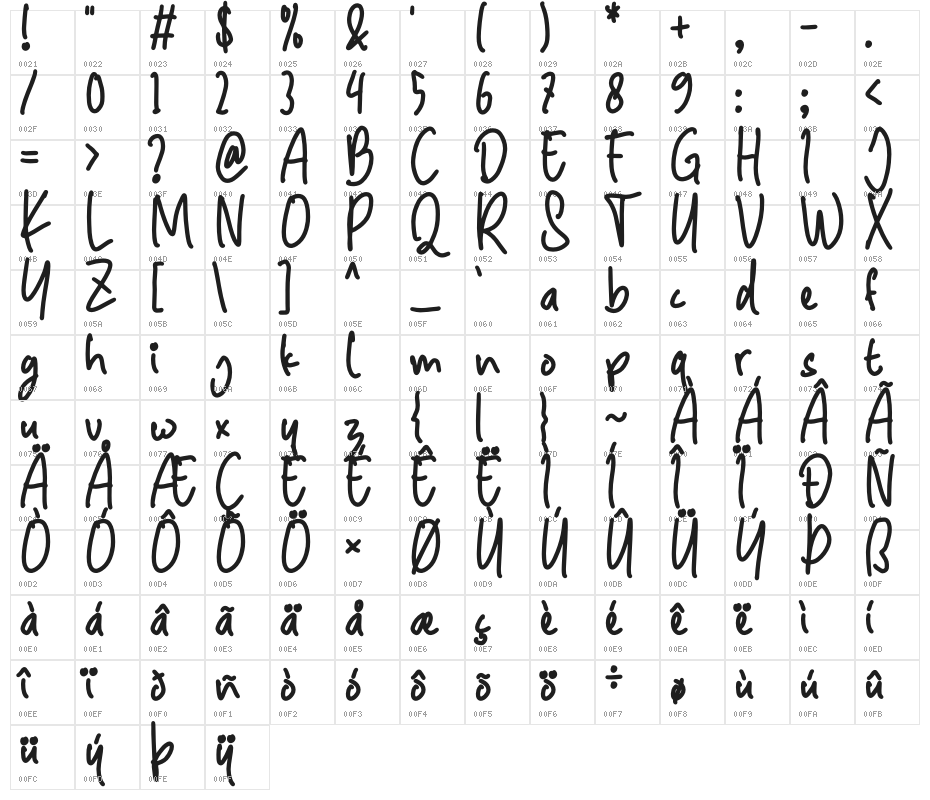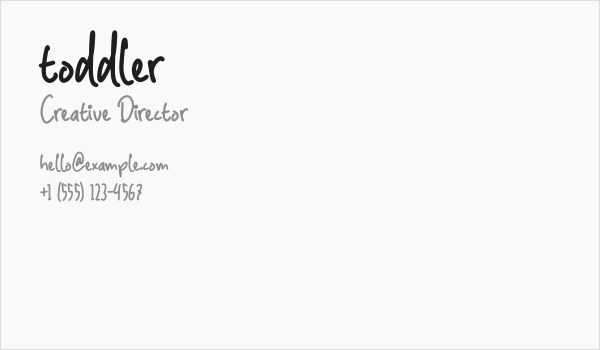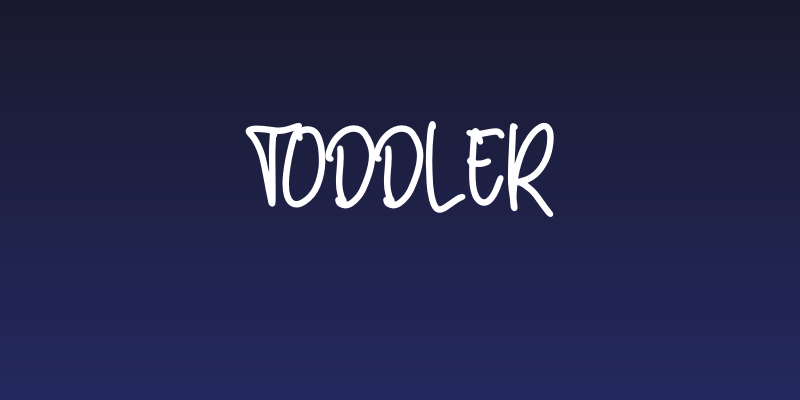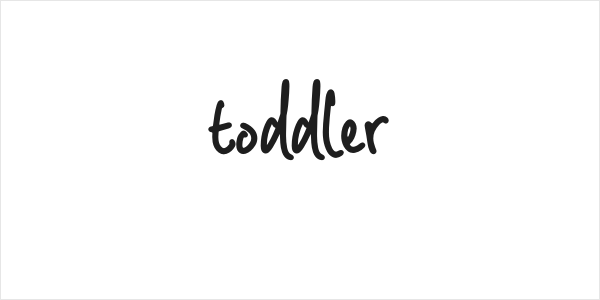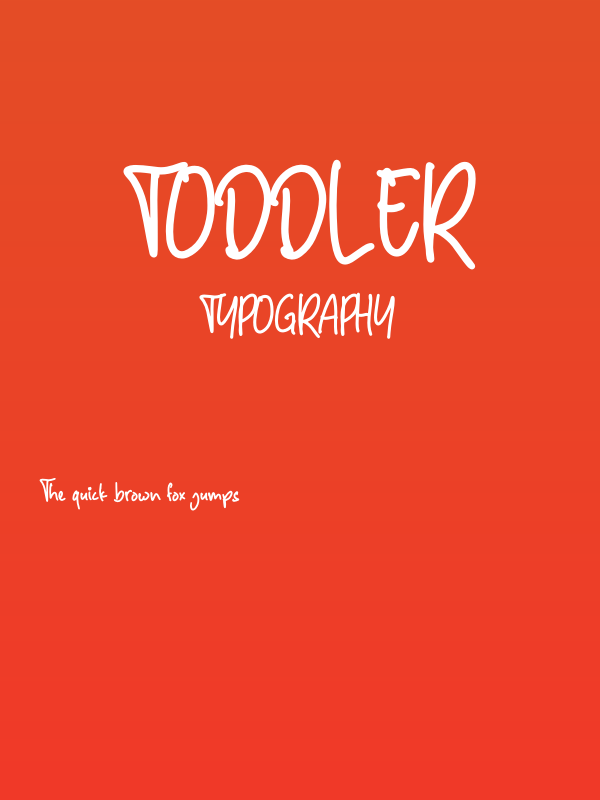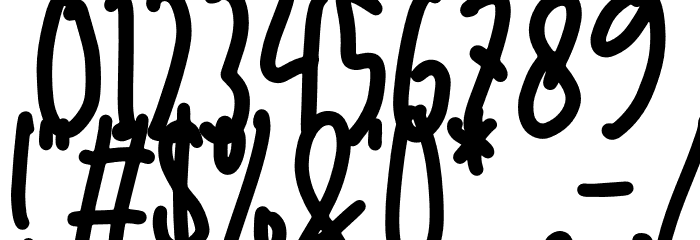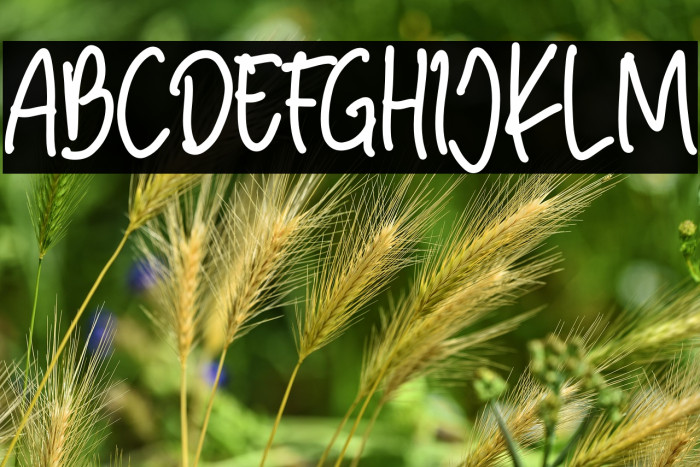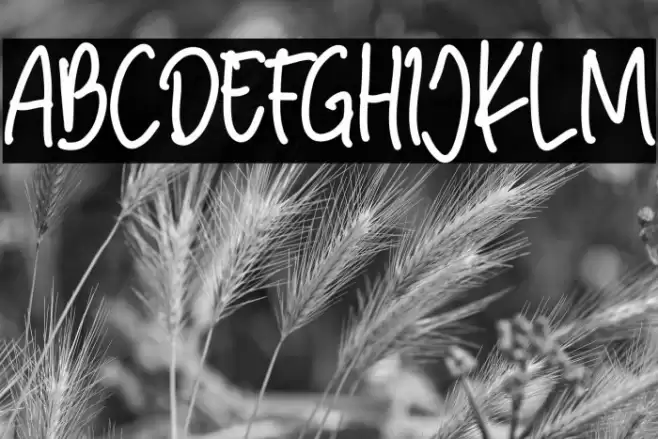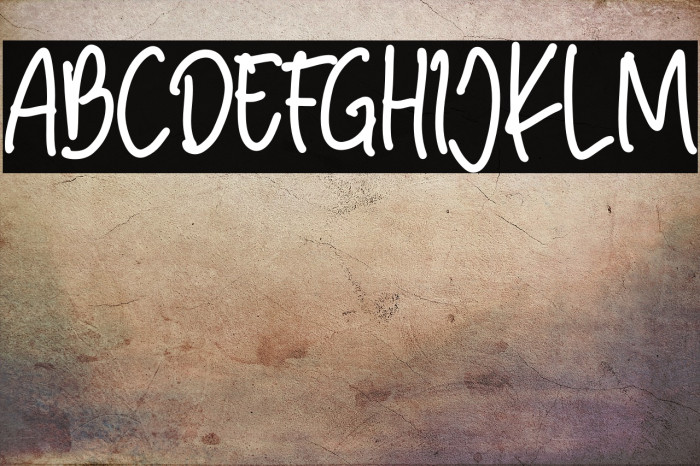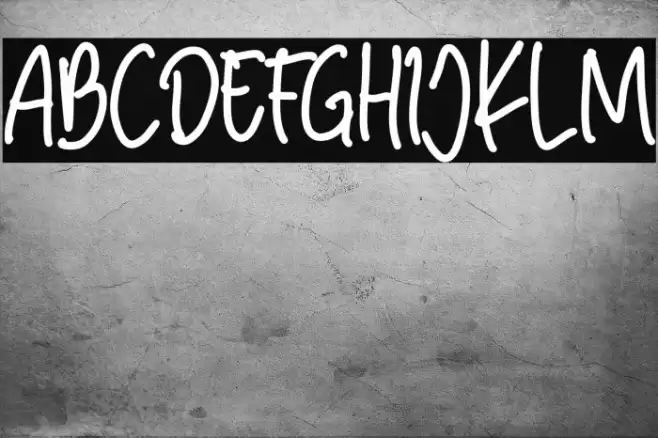
toddler Font
| 全体的なスタイル | Casual, Playful |
| 用途 | Headlines, Logos, Creative projects |
| おすすめプロジェクト | Ideal for children's books, playful branding, casual invitations, and creative social media graphics. |